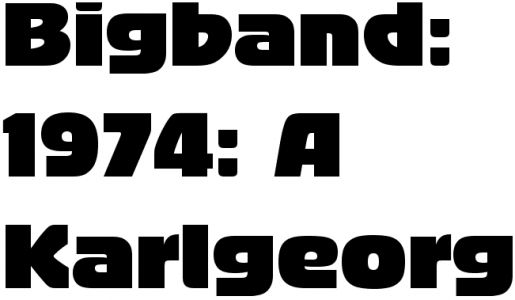
Wolltest Du uns auf eine falsche Fährte locken? Sollte das wirklich die Bigband sein, die ja gar nicht selten zu sehen ist?
Nun denn auf in die nächste Runde. Fürs erste ohne Hilfen.
Genau die. Bravo (ich habe hier aber die preisgünstigere Sauerkrautauto verwendet, das sollte keinen bedeutenden Unterschied gemacht haben).
die sauerkrauto sieht zwar teilweise (vorallem bei den minuskeln) anders aus aber dafür passt der name besser dazu. es gibt auch noch eine dritte, freie schrift, von einer dame deren name ich andauernd vergesse ... :(
kleiner tipp: ein digitaler font, den aber mit großer sicherheit auch bleisetzer schon gesehen haben. die schrift selbst ist noch keine 5 jahre alt.
die sauerkrauto sieht zwar teilweise (vorallem bei den minuskeln) anders aus aber dafür passt der name besser dazu. es gibt auch noch eine dritte, freie schrift, von einer dame deren name ich andauernd vergesse ... :(
Cargo Two SF von Anke Art.
Nicht heulen. Bitte. Ist doch nur ein Spiel. Also gut - die (tatatataa) Logotypia pro eines allseits beliebten Foreninhabers. Ich gebe zu, einen Buchstaben, der nicht in »TYPOFORUM« enthalten ist, hätte ich nicht so leicht erkannt.